针对“字库字体版权”的概念,目前司法领域并无统一的定论。从通常的字面语义角度进行理解,“版权”亦称“著作权”,指作者依法对某一著作物享有的包括署名权、保护作品完整权、修改权、复制权、翻译权在内的一系列权益。若上述权利受到侵犯,作品作者有权要求停止侵权行为和赔偿损失。
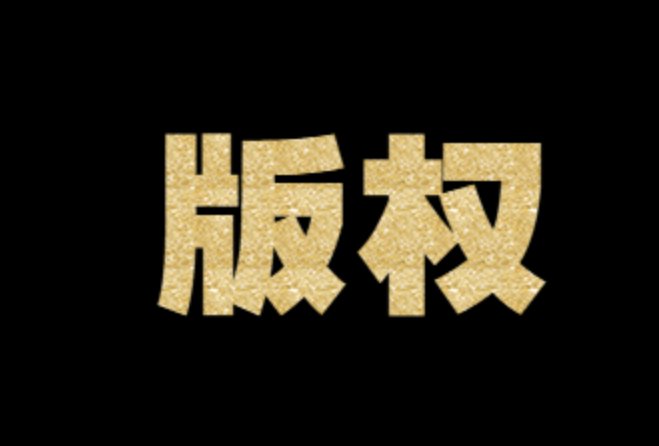
我们都知道现存最早的汉字是约公元前1300年殷商时期的甲骨文,汉字已有六千多年的历史,是全球使用时间最长没有出现断层的文字,汉字是古人象形表意造字唯一传承至今并硕果仅存的文字。汉字的衍生文字越南喃字、西夏文、女真文、契丹文等已消亡,日文只是部分保留汉字。现代汉字分为繁体字和简化字。
“字库”是一个汉语词汇,是中英文字体以及相关字符的电子文字字体的集合库,被广泛用于网络、计算机及相关电子产品中。“字体”则可以被定义为文字的外在表现形式。同一文字可以有不同的表现形态,如日常手写的燕书、隶书、行书、草书等,机器印刷的仿宋、宋体、黑体等等。
将以上概念完整联结起来,我们可以将“字库字体版权”理解为,当字体集合库、文字的外在形态被法律认定为作品时,其创作者即为作者,该作者应受到相关法律保护的权利即为字库字体版权。
电影字幕用的最多的是黑体、其次是楷体;也有用手写字。 电影字...